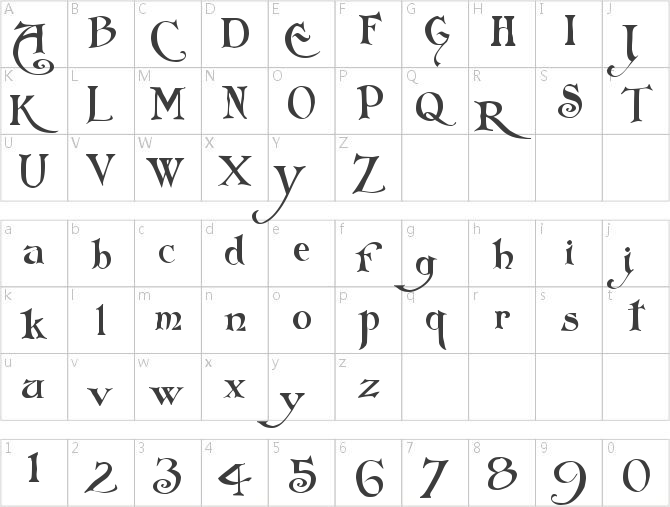
CenturyOldStyle_Bold 詳情頁
CenturyOldStyle_Bold字體字庫是一款讓人賞心悅目、百看不厭的英文字體,適合各類廣告和產(chǎn)品包裝設(shè)計應(yīng)用,字體大小0.06MB,格式為ttf字體,上傳用戶是373790005,作者/版權(quán)方為未知